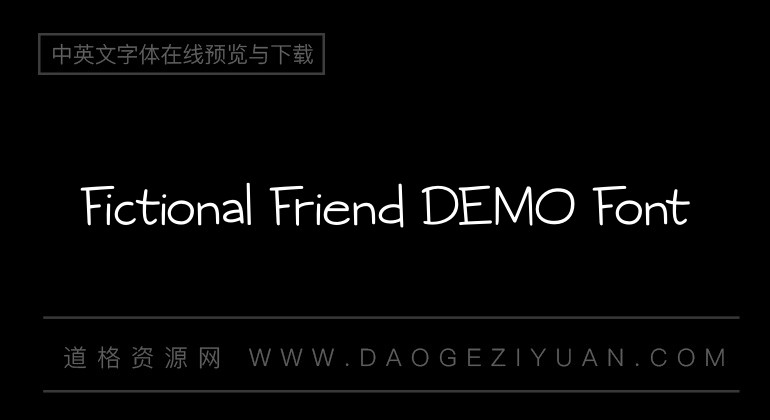
Fictional Friend DEMO Font
Fictional Friend DEMO Font 是一种非常漂亮的字体,具有现代感和创意感。这种字体的设计灵感来自于手写字体和印刷字体,它采用了流畅的线条和简洁的形状,使得它在设计中非常的适用。此字体的字母和数字都非常的清晰,非常适合用于印刷或数字设计领域。此外,它还包含了一些特殊的图标和符号,可以帮助你更好地表达你的想法和意愿。总体来说,Fictional Friend DEMO Font 是一种非常优秀的字体,适合用于各种设计领域,如品牌标识、海报、广告、印刷品等。
Fictional Friend DEMO Font是一款非常不错的手写艺术字体,具有很好的视觉感,适合于文化类的宣传设计、商业类品牌的广告和产品包装设计以及个性化文字排版等较多场景。